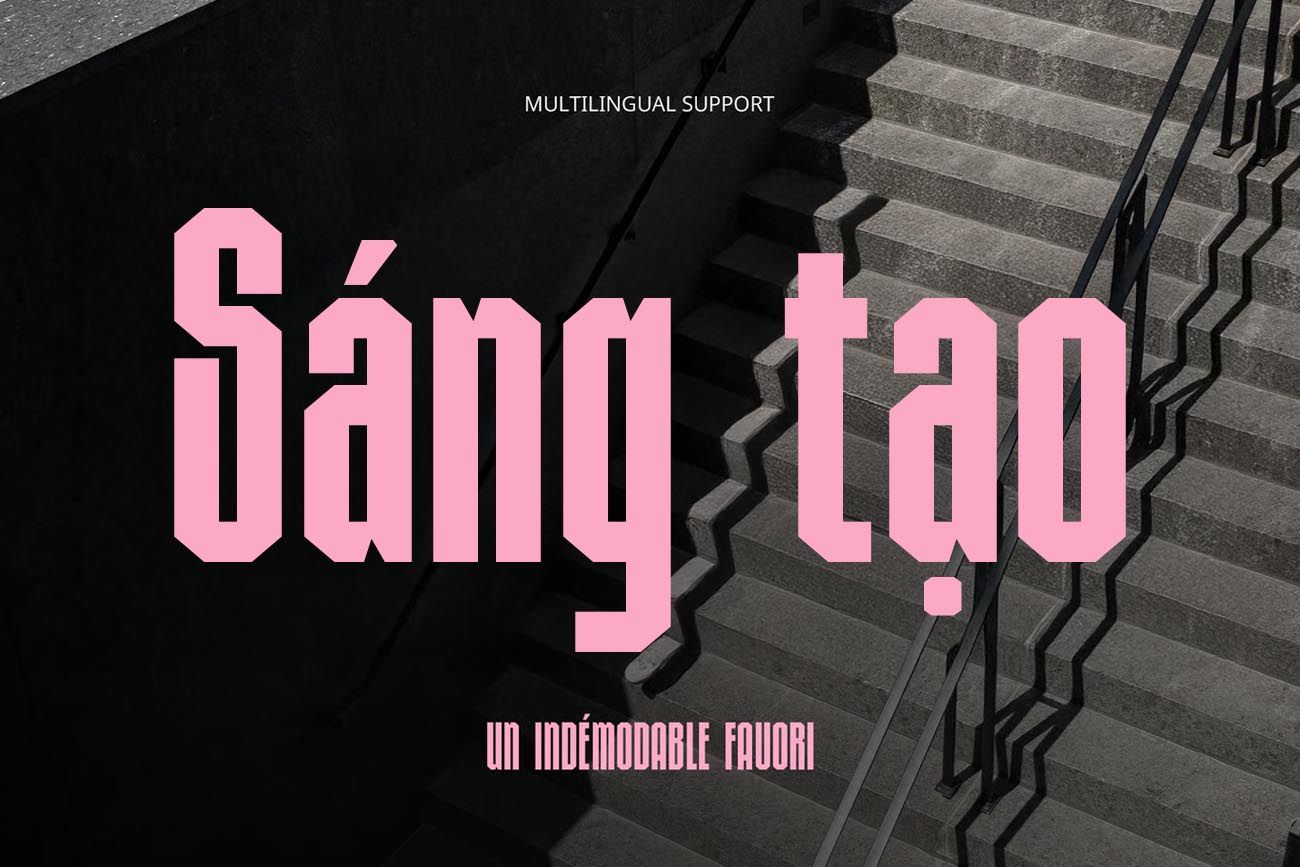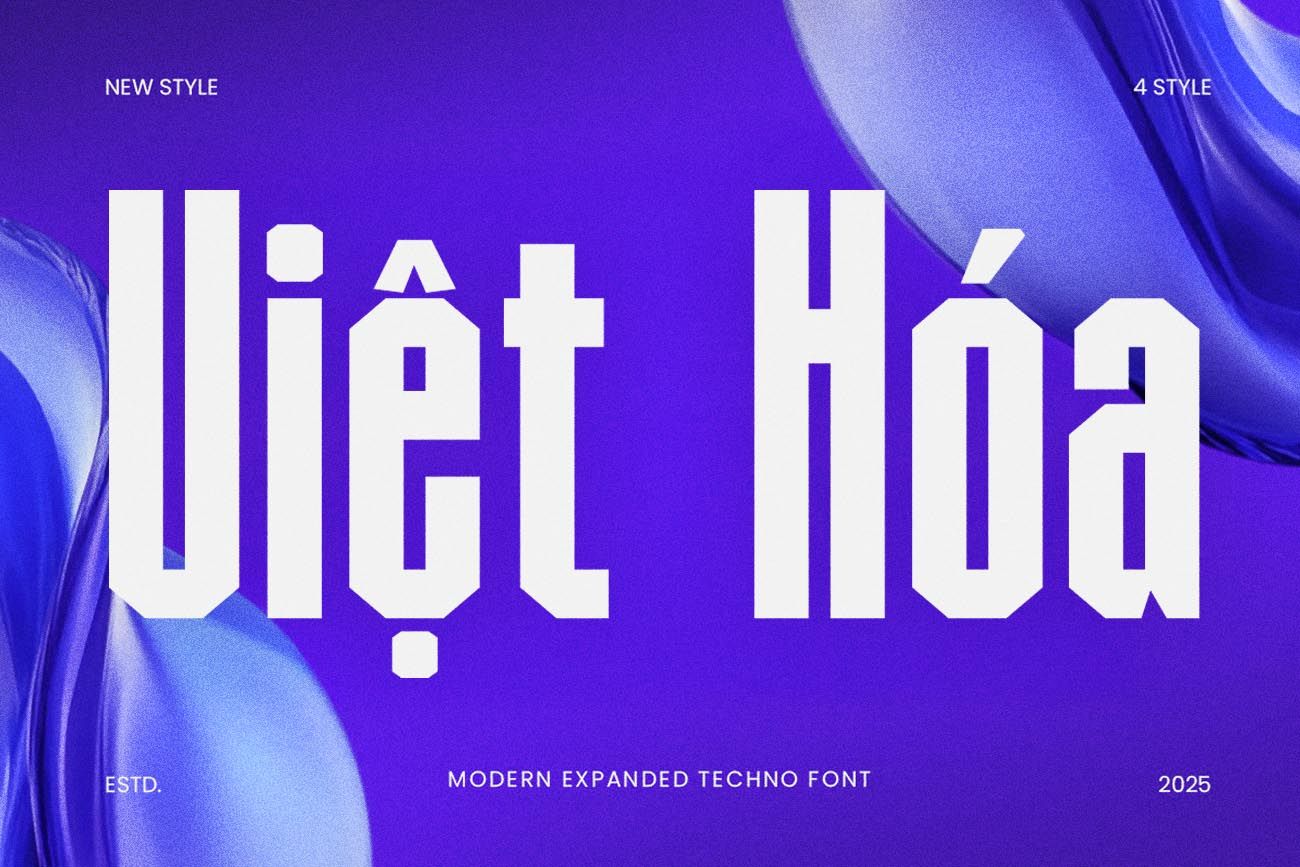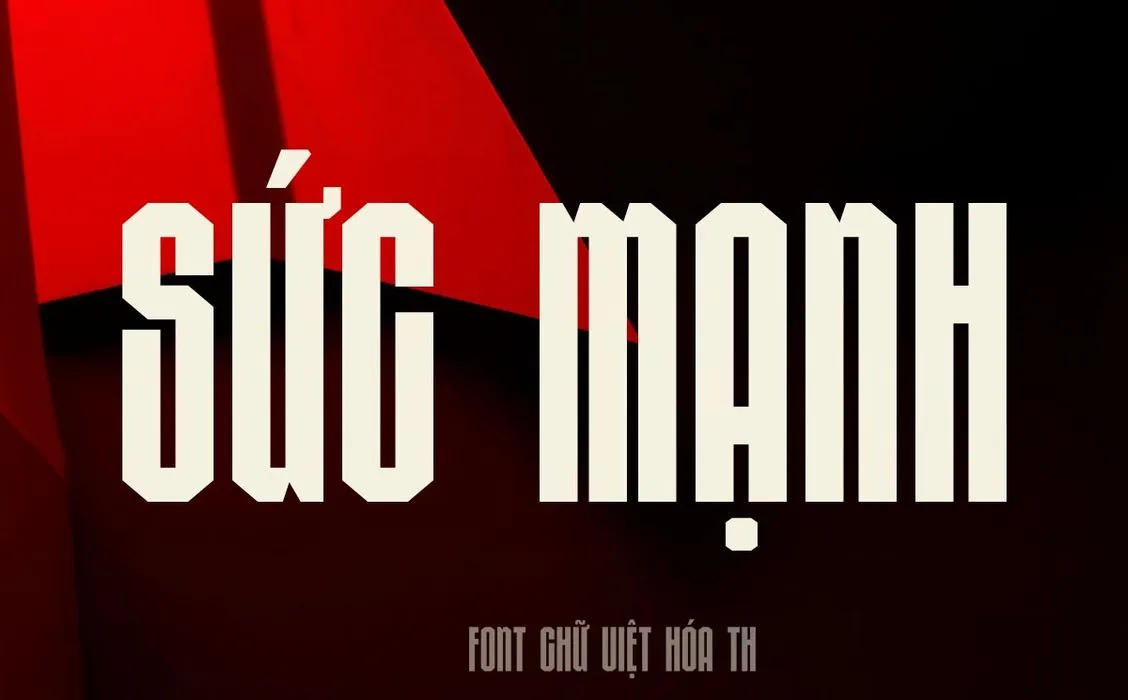
[Tải Xuống] Font Chữ Không Chân TH Glister Việt Hóa – Cứng Cáp, Mạnh Mẽ
Nếu bạn đang tìm kiếm một font chữ không chân mang đến cảm giác mạnh mẽ, hiện đại và nổi bật, thì TH Glister là lựa chọn rất đáng thử. Font sở hữu kiểu dáng đậm, thuôn gọn, đường nét cứng cáp và đầy cá tính – đặc biệt phù hợp cho các thiết kế tiêu đề, logo hoặc thương hiệu cần tạo ấn tượng mạnh ngay từ ánh nhìn đầu tiên.
Font Glister thuộc nhóm sans-serif hiển thị (display sans), được thiết kế bởi Craft Supply Co. – một studio nổi tiếng trong giới thiết kế font chữ hiện đại. Với cấu trúc condensed (thuôn dài), đường nét dày và bo gọn, font mang lại sự vững chắc và dứt khoát trong từng con chữ. Đây là dạng font chữ cứng cáp lý tưởng cho các thiết kế đề cao tính rõ ràng, chắc chắn và hiện đại.
Tổng thể font giúp người xem cảm nhận rõ ràng về sự mạnh mẽ, chuyên nghiệp và có định hướng thị giác rõ nét – rất phù hợp cho tiêu đề poster, banner mạng xã hội, lookbook thời trang hoặc bao bì sản phẩm cao cấp.
Điểm đặc biệt của font Glister là đã được Phạm Sơn – Admin của Fontdep.vn và S99.vn – Việt hóa trọn bộ. Font hỗ trợ đầy đủ dấu tiếng Việt, bao gồm các ký tự đặc biệt như “ă, â, ê, đ…” với thiết kế chỉn chu, đồng bộ về phong cách. Điều này giúp nhà thiết kế dễ dàng ứng dụng font trong các sản phẩm thuần Việt mà không lo lỗi ký tự hay vỡ bố cục.